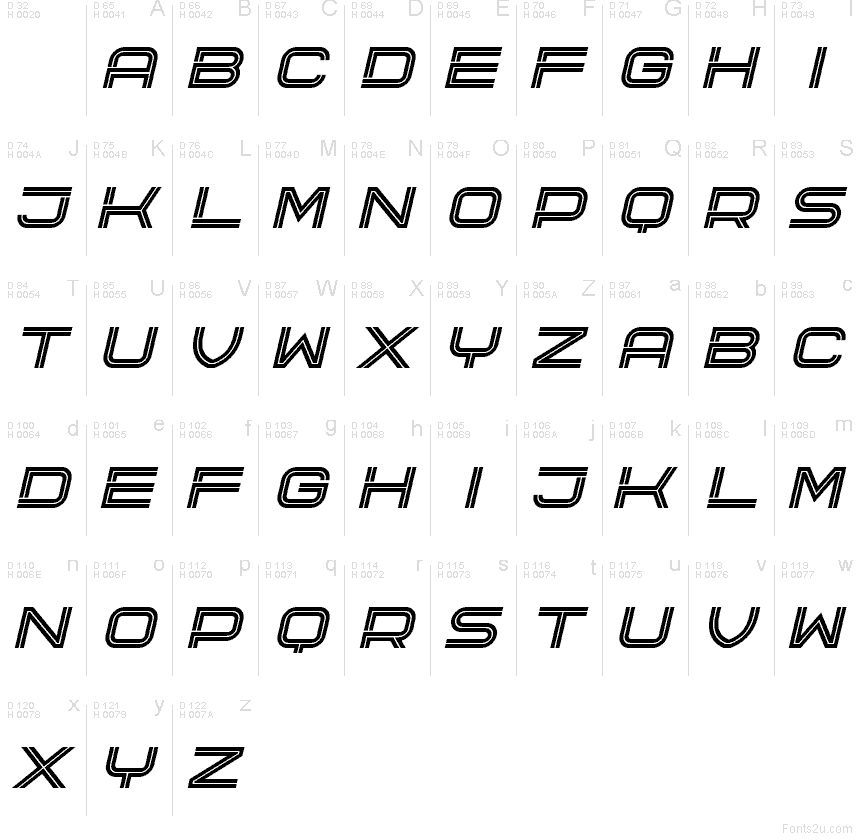
Haine Exravagant Italic od Vladimira Nikoliće je bezplatné techno display písmo definované rychlými, doprava nakloněnými siluetami s vícenásobnými paralelními obrysy. Tyto opakující se pruhy mění každé písmeno ve vrstvenou stopu plnou negativního prostoru a dodávají designu elegantní, strojový rytmus namísto pouhého náklonu kurzívy.
Lineární konstrukce písma je ideální pro krátké titulky v herních překryvech, sci-fi plakátech, DJ letácích, úvodních obrazovkách aplikací a e-sportovním brandingu. Zároveň dodává ostrost logům a nadpisům, které potřebují pohyb, aniž by ztratily svůj geometrický řád.
Haine Exravagant